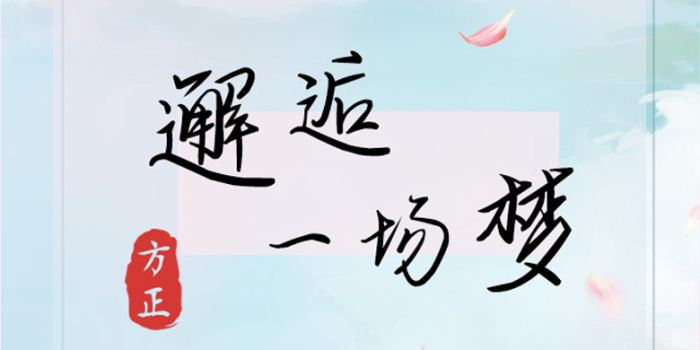
方正手跡-邂逅一場夢由方正字庫俞亦婷設(shè)計師出品的藝術(shù)字體,該字筆溫潤婉轉(zhuǎn),結(jié)構(gòu)張弛有度,似在敘說纏綿悱惻的愛情故事,適合應(yīng)用于藝術(shù)設(shè)計、平面宣傳設(shè)計、網(wǎng)頁設(shè)計,書法等領(lǐng)域。
誰的青春不做夢,而那些夢里一定有愛情。該用筆溫潤婉轉(zhuǎn),結(jié)構(gòu)張弛有度,似在敘說纏綿悱惻的愛情故事。適用于文藝類的書刊、品牌廣告和產(chǎn)品包裝設(shè)計,以及社交網(wǎng)絡(luò)的個性化用字。。。